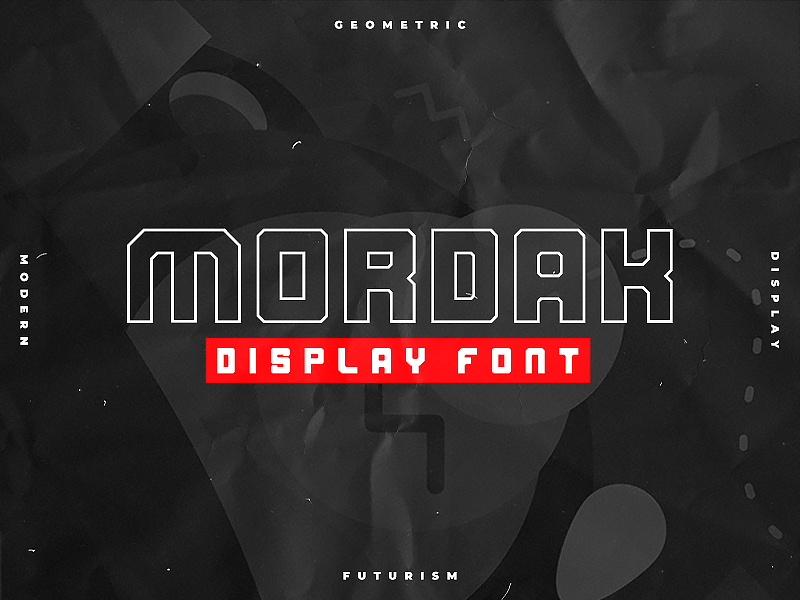
Aqui está uma descrição envolvente para a página de download da fonte ‘Mordak Typeface’, no estilo solicitado: O Mordak é uma tipografia sans-serif de grande contraste que combina formas geométricas e um toque futurista, criando um design moderno com forte impacto visual. Seu uso pode ser revolucionário para projetos digitais ou impressos, especialmente quando combinado com elementos do universo do android ou robôs. Ideal tanto para trabalhos de arte digital quanto para criações em papel, este tipo de fonte é perfeito para designers que buscam uma abordagem futurista e geométrica. Seu uso permite criar designs atraentes e inovadores, especialmente no campo das tecnologias móveis e robótica. O Mordak é um complemento ideal para qualquer projeto visando um estilo moderno, com elementos sci-fi, prometendo uma impressão única e impactante. Para designers que buscam trazer algo novo à tabela do design gráfico, o Mordak pode ser a solução perfeita. Não apenas respeitamos seu talento, também valorizamos sua capacidade de inovar em cada projeto criativo. Com a Mordak Typeface na sua paleta de ferramentas, você está garantido um estilo único e impressionante para seus projetos.